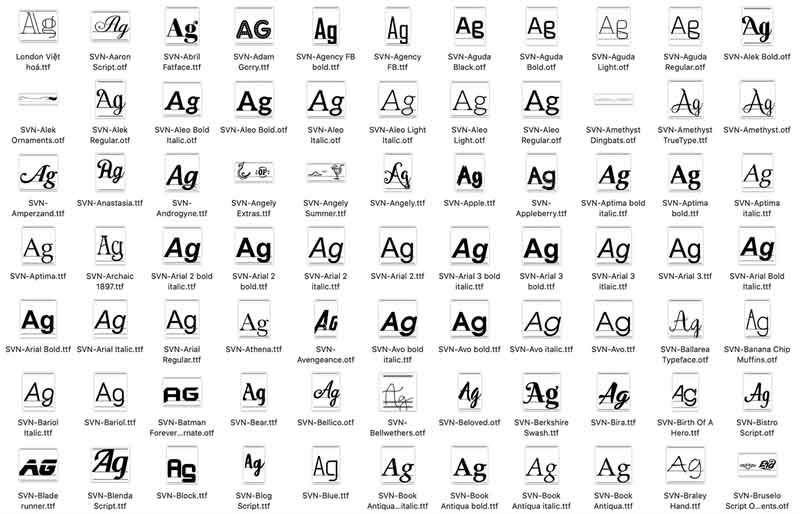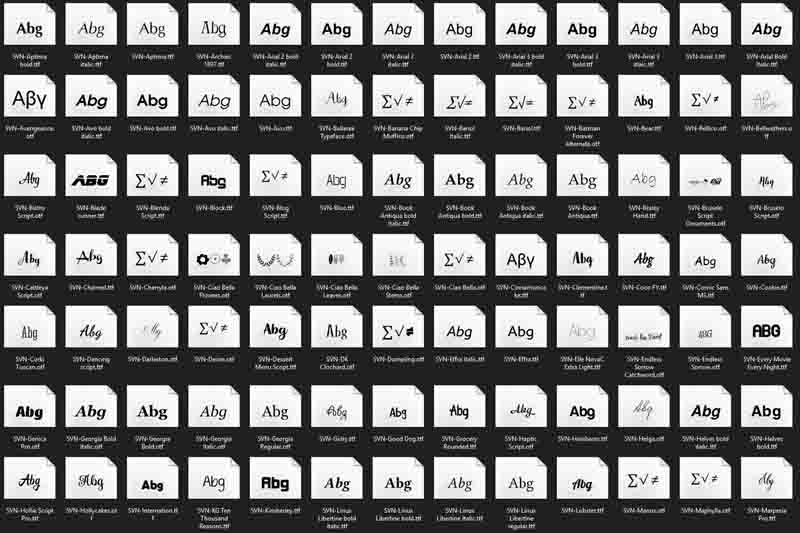
Bạn đang tìm một font chữ phù hợp cho nhu cầu cá nhân của mình? Bài viết sau đây sẽ chia sẻ đến bạn những font chữ nghệ thuật Việt hoá đang thịnh hành hiện nay.
Thiết kế font chữ nghệ thuật việt hóa đẹp
Font chữ nghệ thuật Việt hóa mang đến sức hút đặc biệt trong các thiết kế sáng tạo, từ poster đến thiệp mời, bao bì sản phẩm hay các ấn phẩm thương hiệu. Những font này không chỉ hỗ trợ đầy đủ các ký tự tiếng Việt mà còn thể hiện cá tính và phong cách riêng cho từng dự án.
Các bộ font chữ nghệ thuật đẹp
Bộ font chữ nghệ thuật Việt Hóa cực đẹp 1
Bộ font chữ nghệ thuật đẹp 2
Bộ font chữ nghệ thuật đẹp 3
Bộ font chữ nghệ thuật đẹp 4
Các bộ font chữ nghệ thuật đẹp thường gặp trên máy tính
Bộ font chữ nghệ thuật đẹp 5
Bộ font chữ nghệ thuật đẹp 6
Bộ font chữ nghệ thuật đẹp 7
Bộ font chữ nghệ thuật đẹp 8
Bộ font chữ nghệ thuật đẹp 9
Tham khảo thêm bộ font chữ nghệ thuật đẹp khác
Bộ font chữ nghệ thuật đẹp 10
Bộ font chữ nghệ thuật đẹp 11